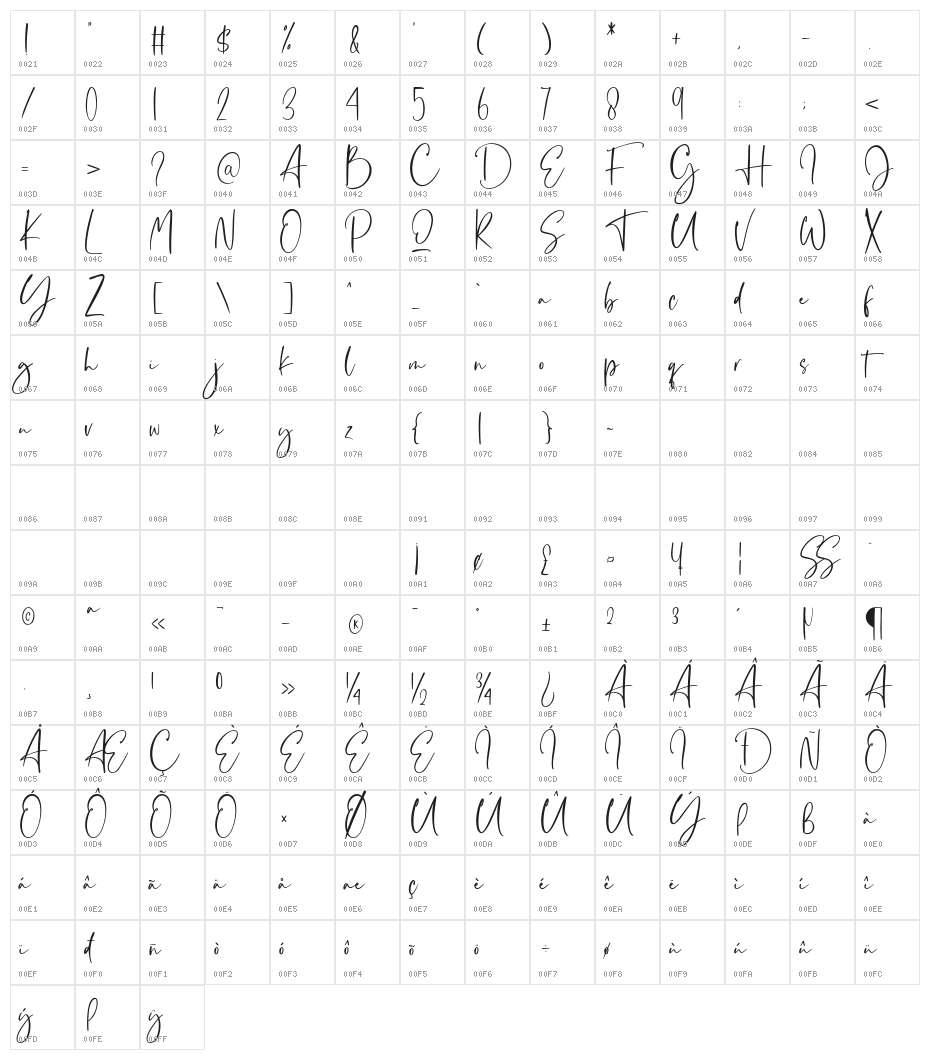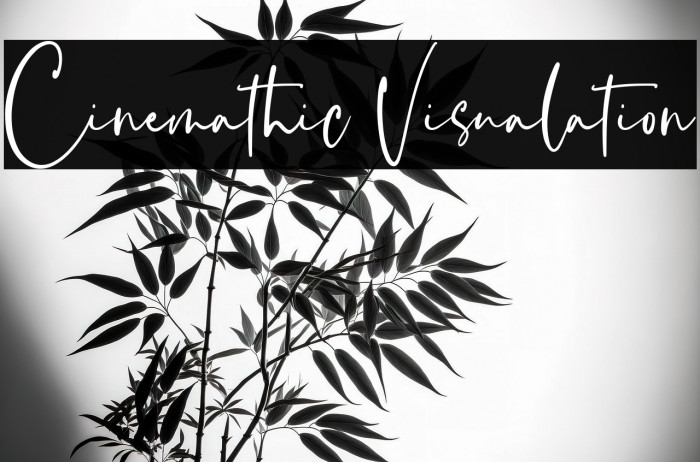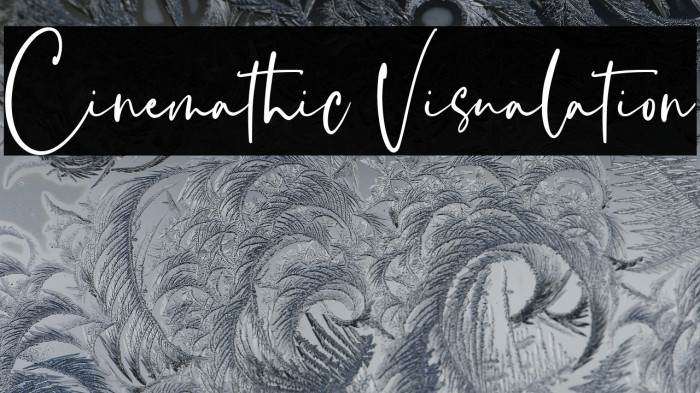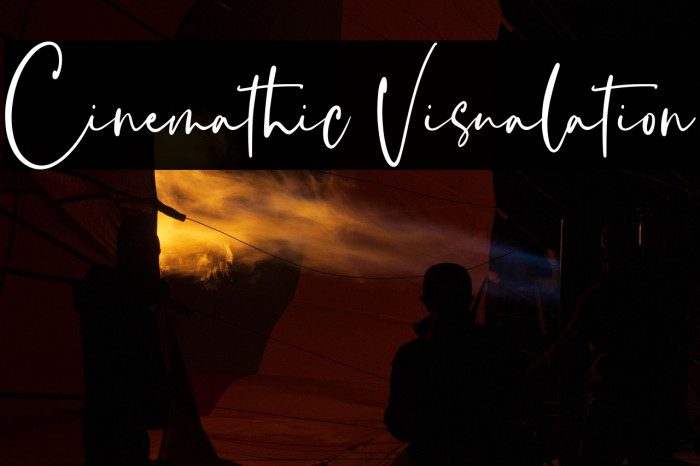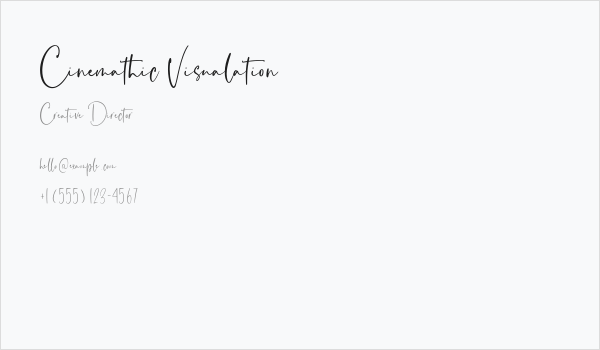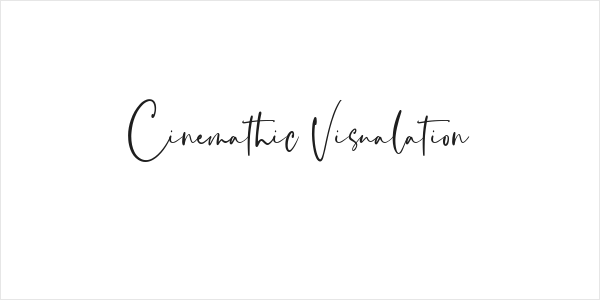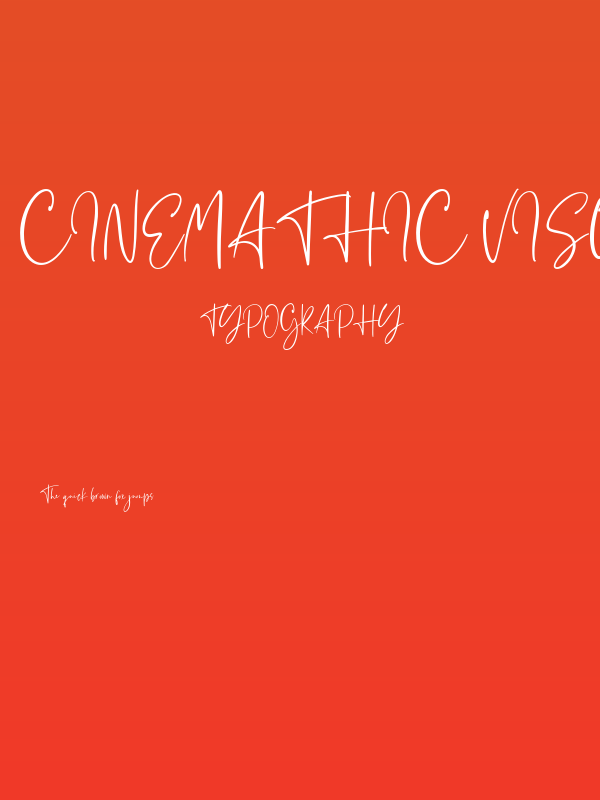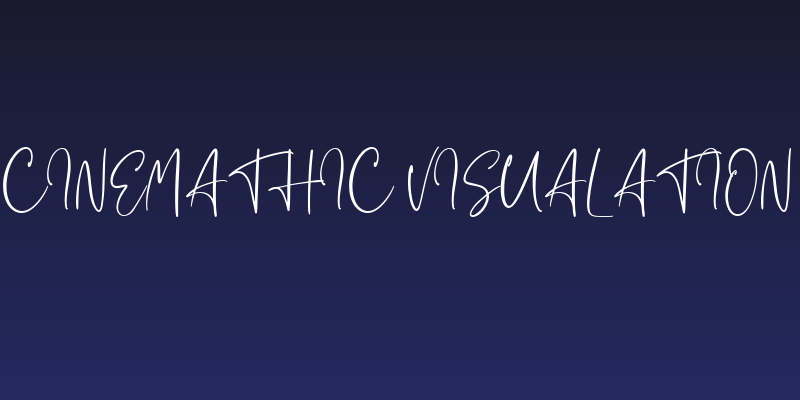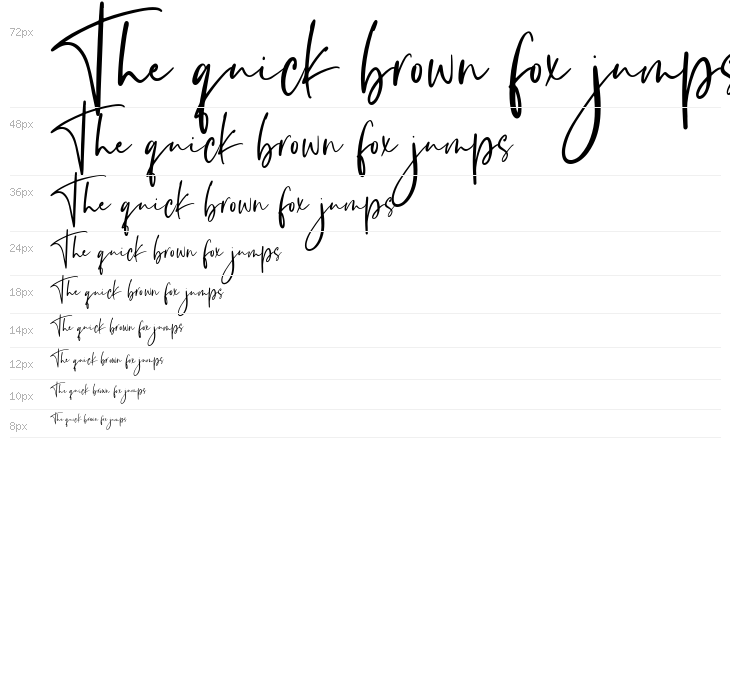
Cinemathic Visualation Font
| Stile generale | Casual and artistic |
| Caso d'uso | Logos, invitations, personal projects |
| Progetti proposti | Greeting cards, invitations, personal branding. |